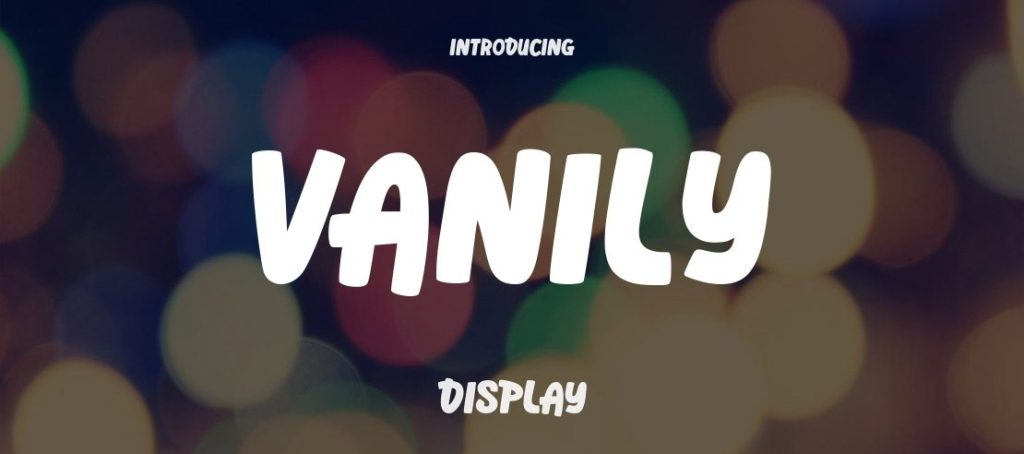
Tác giả: Kurnia Setyadi
Ngày phát hành: 2024
Việt hóa: Việt Hóa
Bộ Font: Font 1FTV
Phân loại: Sang trọng
Độ dày: Thin, Light, Regular, Bold
Font 1FTV Vanily là một trong những loại chữ độc đáo và tinh tế, thuộc bộ font chữ 1FTV mang đến sự thương mại và thanh lịch trong từng đường nét. Phông chữ này được thiết kế cho các đặc điểm nổi bật như đường nét nhẹ nhàng nhẹ nhàng, dễ đọc nhưng vẫn giữ vẻ đẹp nghệ thuật, phù hợp cho các dự án thiết kế sáng tạo, mời, hoặc tiêu đề trang web. Với sự kết hợp hoàn hảo giữa tính thẩm mỹ và tính ứng dụng, font 1FTV Vanily chắc chắn sẽ là lựa chọn tuyệt vời cho những ai đang tìm kiếm sự khác biệt và tinh tế trong thiết kế đồ họa.